ポップフォント日本語おすすめ8選
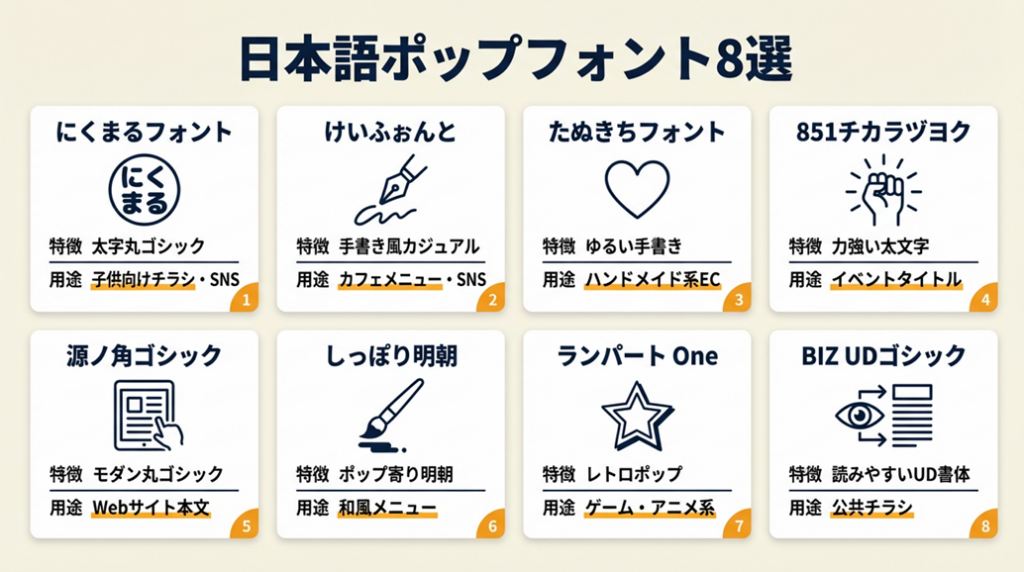
商用利用可の国産フォントは着実に増えています。用途に合った1本を選ぶことで、デザイン全体のクオリティが一段上がります。
にくまるフォントは太字丸ゴシックの定番
にくまるフォントはフォントなで配布されており、個人・商用ともに無料で利用できます。ライセンスはM+ FONTS LICENSEに準じており、印刷物・デジタルコンテンツともに商用・非商用を問わず使用できます。太めの丸ゴシックでインパクトがあり、子供向けチラシやSNSサムネイルに特に向いています。かわいい日本語フォントをさらに幅広く探したい場合は、かわいい無料フォント10選も参考になります。
線の太さがほぼ均一なため、小サイズのテキストでも視認性が保たれます。ポスターのタイトルだけでなく、本文サイズでも崩れにくいのが強みです。
Canva公式クリエイターとして活動するグラフィックデザイナーは「にくまるは、丸みがあって親しみやすい手書きフォントです。楽しい雰囲気を出したいときに最適」と振り返っています(デザイナーがおすすめ!本当に頼れるCanvaの無料フォント17選)。
けいふぉんとは手書き風カジュアルの代表格
けいふぉんとはアニメ「けいおん!」のロゴをヒントに制作されたフォントで、制作者Do-FontによるすもももじサイトやFontFreeなどで配布されています。ライセンスはApache License 2.0で、商用利用可・クレジット表記はライセンス条件に従う必要があります(SIL OFLではない点に注意してください)。軽快でポップな文字デザインが特徴で、カフェメニューや手作り感を出したいSNS投稿に向いています。字間が広めに設定されているため、狭いスペースへの配置には事前にテキストプレビューで確認してください。
ほかにも選べる日本語ポップフォント6選
| フォント名 | 配布元 | 特徴 | 向いているケース |
|---|---|---|---|
| たぬきちフォント | フォントポ | 手書き・ゆるい印象 | ハンドメイド系EC |
| 851チカラヅヨク | フォントポ | 力強い太文字 | イベントタイトル |
| 源ノ角ゴシック | Google Fonts | モダン丸ゴシック | Webサイト本文 |
| しっぽり明朝 | Google Fonts | ポップ寄り明朝 | 和風メニュー |
| ランパート One | Google Fonts | レトロポップ | ゲーム・アニメ系 |
| BIZ UDゴシック | Google Fonts | 読みやすいUD書体 | 公共チラシ・福祉 |
Q: 日本語ポップフォントで一番汎用性が高いのはどれですか?
A: にくまるフォントです。太さと視認性のバランスがよく、印刷物・デジタル両方で安定しています。
ポップフォント英語おすすめ7選
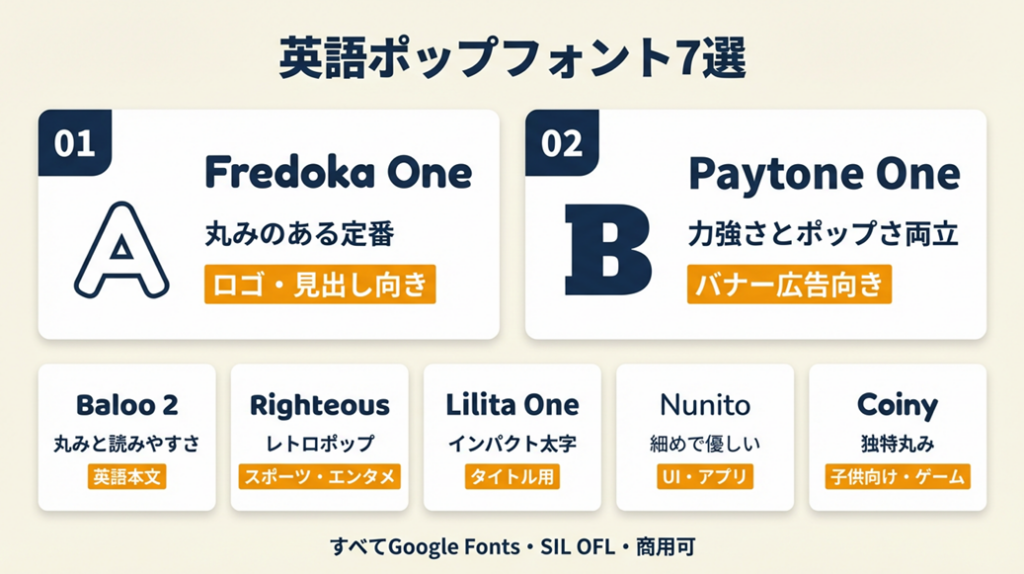
英語ポップフォントは日本語フォントと組み合わせることで、デザインにメリハリが生まれます。日本語フォントが決まる前に英語フォントだけ選ぶと、後でバランスが合わなくなるケースがあります。日本語フォントを先に決め、その印象軸に合わせて英語フォントを選んでください。
Fredoka Oneは丸みのある英語ポップの定番
Fredoka OneはGoogle Fontsで提供されており、SIL OFLライセンスでWebフォントとしても使用できます。デザイナーMilena Brandaoによって制作されたフォントで、大文字のインパクトが強く、ロゴタイプや見出しに向いています。日本語の丸ゴシック系フォントと相性がよく、にくまるフォント+Fredoka Oneの組み合わせが特に安定しています。無料英語フォントの選び方をさらに深く知りたい場合は、無料英語フォント厳選5選も参考になります。
Paytone Oneは力強さとポップさを両立
Paytone OneはFredoka Oneより字幅が広く、横長レイアウトのバナー広告に向いています。Google Fontsで配布されており商用利用可です。線が太くコントラストが強いため、暗い背景色の上に白抜きで使う用途に特に適しています。
ほかにも選べる英語ポップフォント5選
| フォント名 | 配布元 | 特徴 | 向いているケース |
|---|---|---|---|
| Baloo 2 | Google Fonts | 丸みと読みやすさを両立 | 英語本文・長文 |
Q: 手書き風フォントでおすすめはありますか?
A: 日本語では「けいふぉんと」と「たぬきちフォント」が商用利用可で人気があります。英語では「Pacifico」(Google Fonts)が手書き風でありながら視認性が高いため、見出しに使いやすいフォントです。